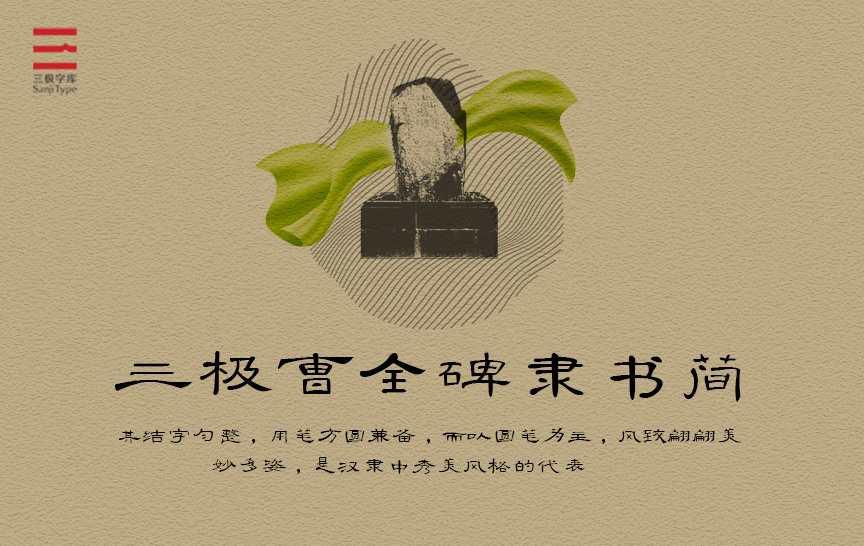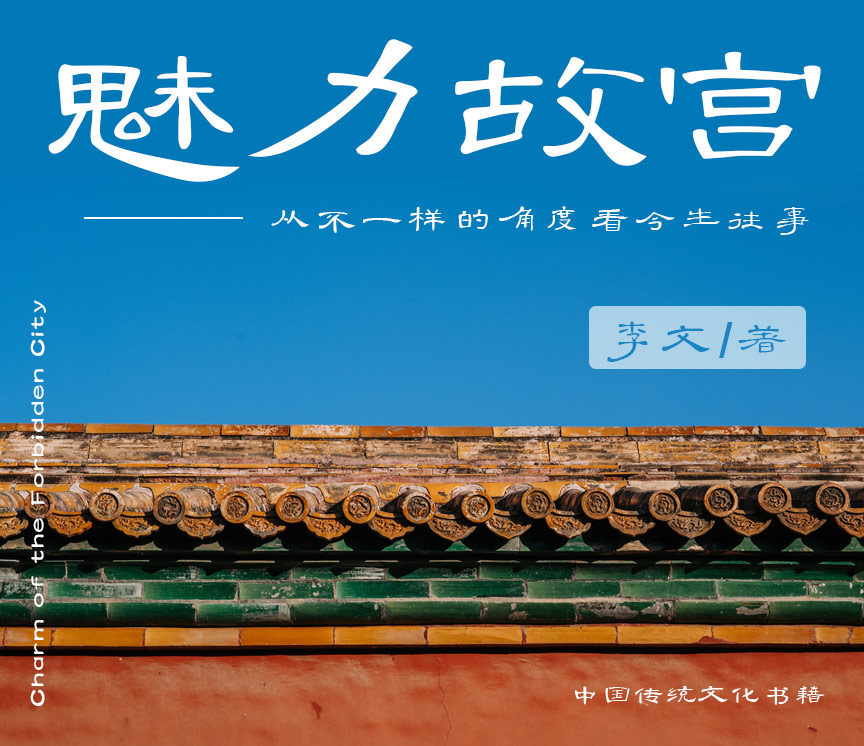
三极曹全碑隶书简
蔡建文
隶书
《曹全碑》属东汉末隶书完全成熟期的代表作品之一,它记载了东汉末年曹全镇压黄巾起义的事件,是研究东汉末年农民起义重要的历史资料,也是现存中国汉代石碑中保存比较完整、字体比较清晰的少数作品之一。其结字匀整,用笔方圆兼备,而以圆笔为主,风致翩翩,美妙多姿,是汉隶中秀美风格的代表。